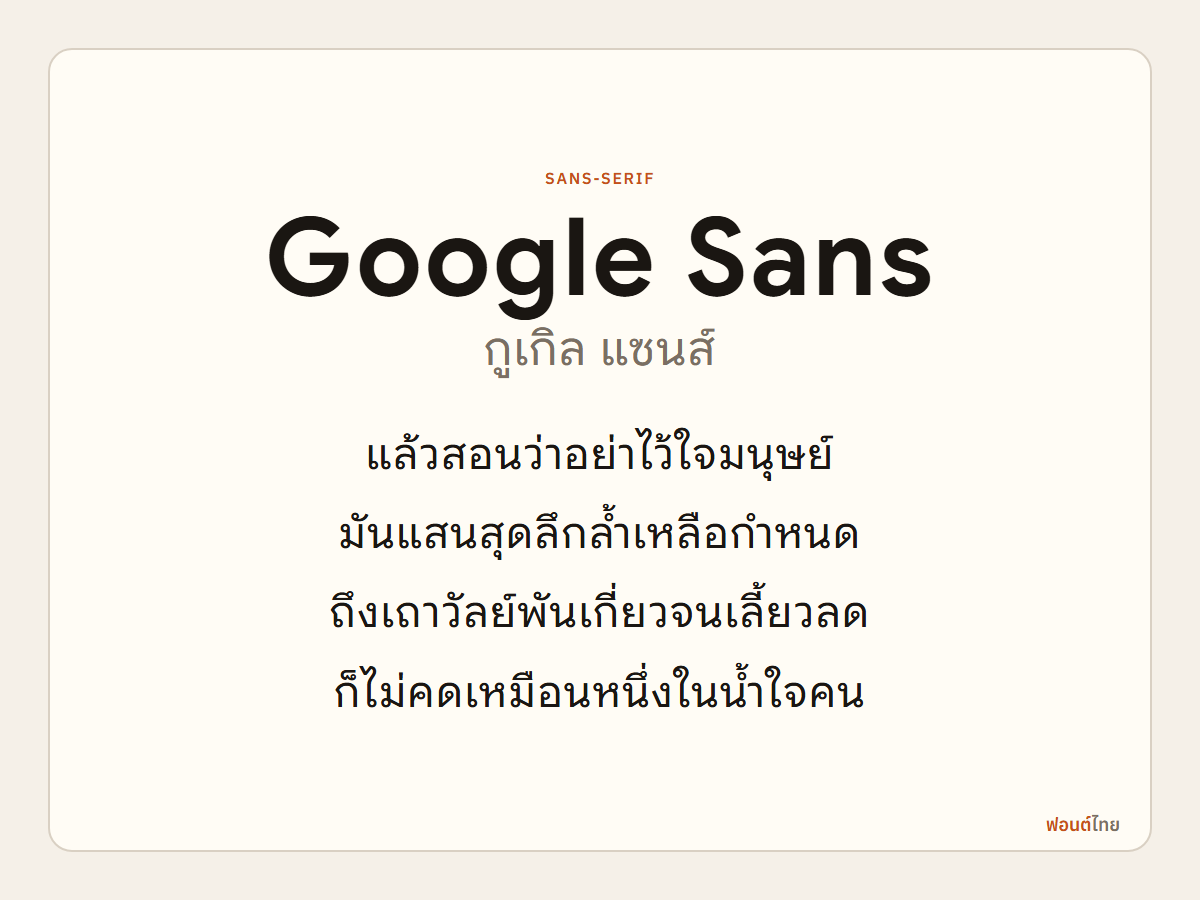
Google Sans กูเกิล แซนส์
ฟอนต์ทางการของ Google สะอาดตา อ่านง่าย
Google Sans เป็นฟอนต์ทางการที่ Google ใช้ในผลิตภัณฑ์ต่างๆ ออกแบบมาให้อ่านง่ายบนหน้าจอทุกขนาด มีความสะอาดตาและเป็นมืออาชีพ
เหมาะสำหรับ: เว็บไซต์แอปพลิเคชันUIองค์กร
sans-serif Variable Font 4 weights + italic
นี่คือตัวอย่างการใช้งานฟอนต์ Google Sans ในขนาด 18px สำหรับเนื้อหาบทความ อ่านง่ายสบายตา เหมาะกับเว็บไซต์และแอปพลิเคชัน
ฟอนต์ Google Sans ขนาดเล็ก — เหมาะสำหรับ caption และคำอธิบายใต้ภาพ
ทำไมฟอนต์ Google Sans ถึงเป็นที่นิยม?
ฟอนต์ Google Sans เป็นหนึ่งในฟอนต์ไทยที่ได้รับความนิยมมากที่สุดบน Google Fonts เพราะมีความสวยงาม อ่านง่าย และรองรับภาษาไทยได้ครบถ้วน
หากคุณกำลังมองหาฟอนต์สำหรับเว็บไซต์หรืองานออกแบบ Google Sans เป็นตัวเลือกที่ดี มีหลายน้ำหนักให้เลือกใช้ ตั้งแต่ Light ไปจนถึง Bold
ฟอนต์ Google Sans มีกี่ตัวหนา (weights)?
มี 4 weights ได้แก่: 400, 500, 600, 700 — weight 700 คือ Bold